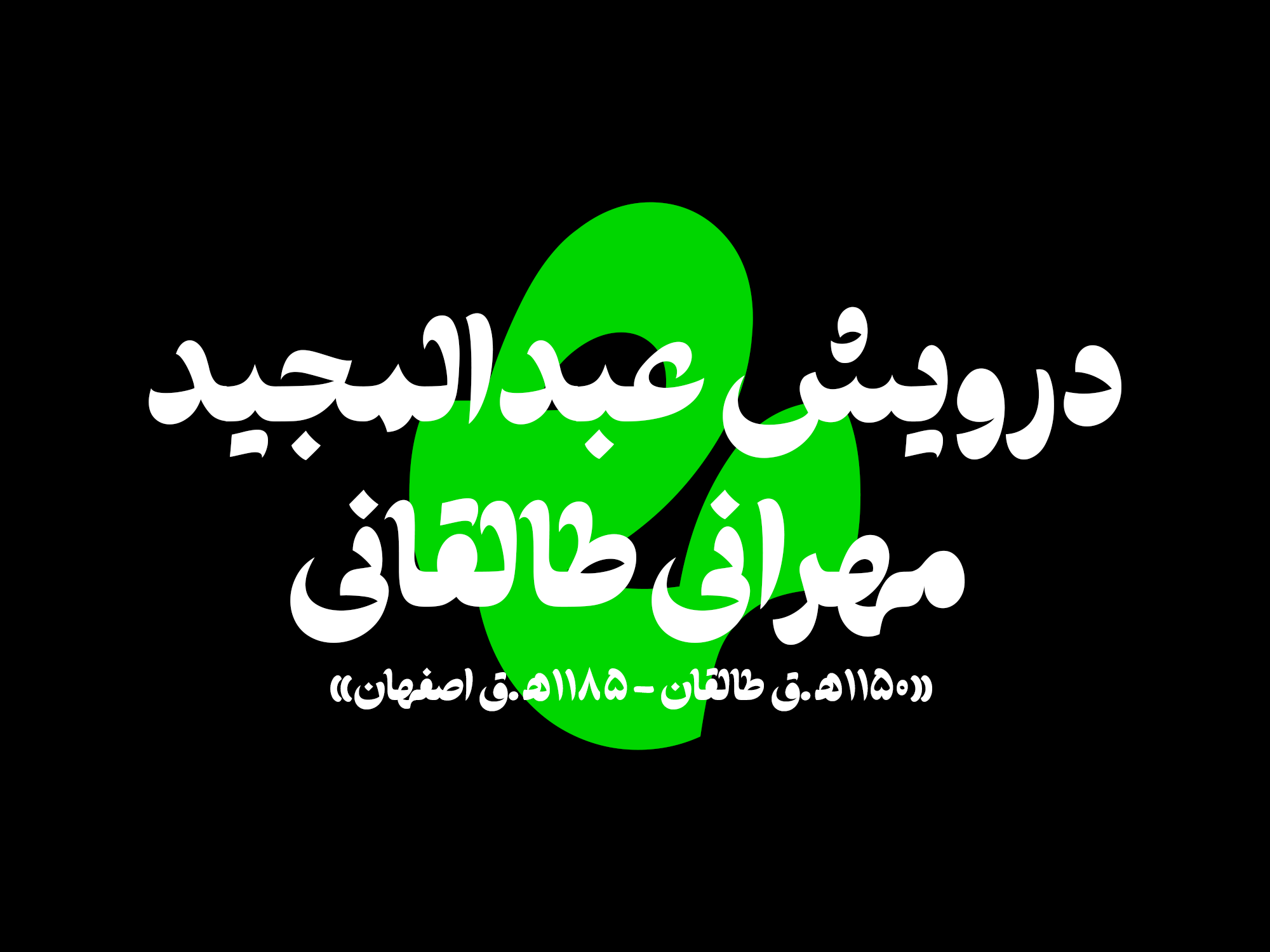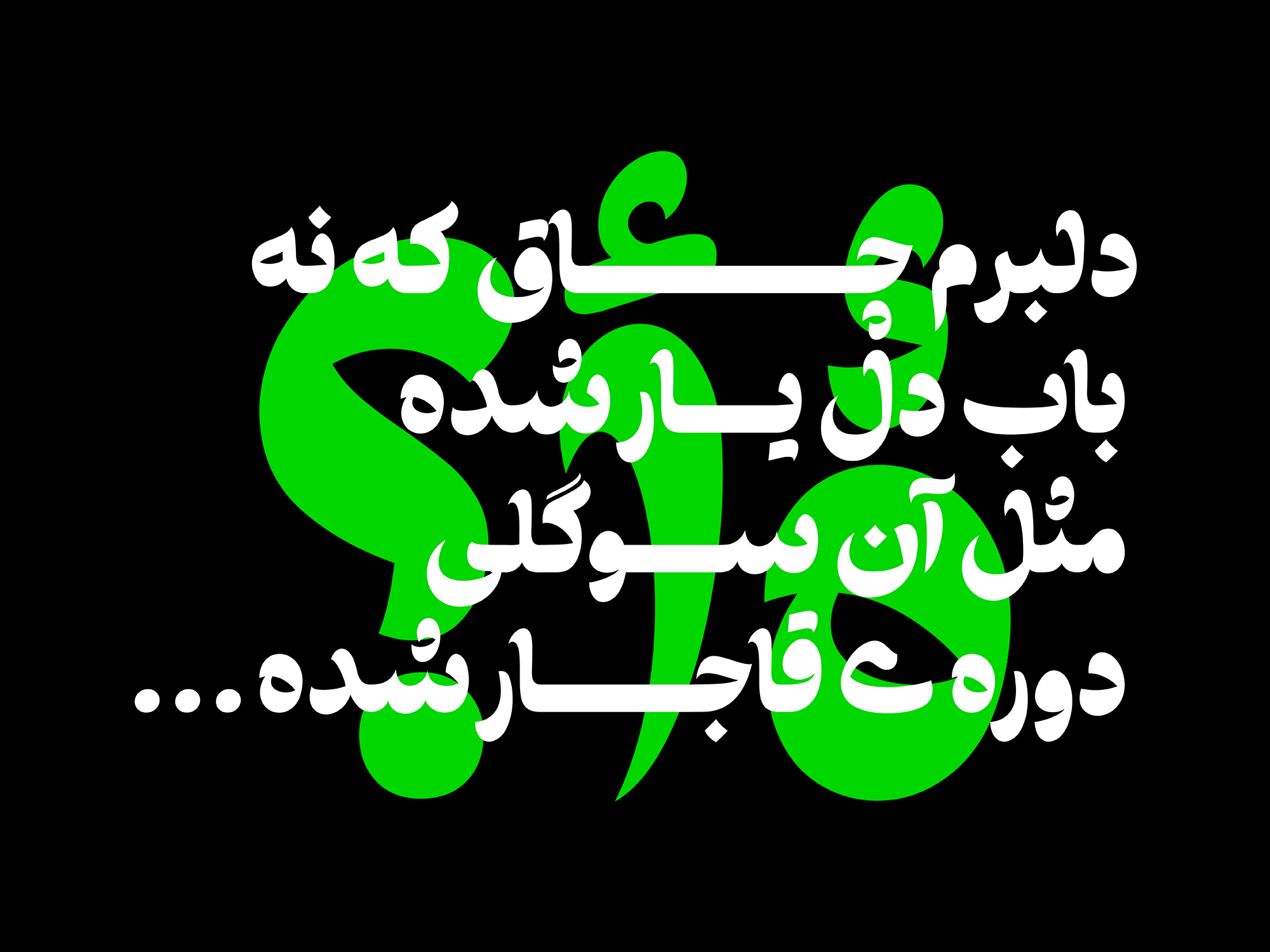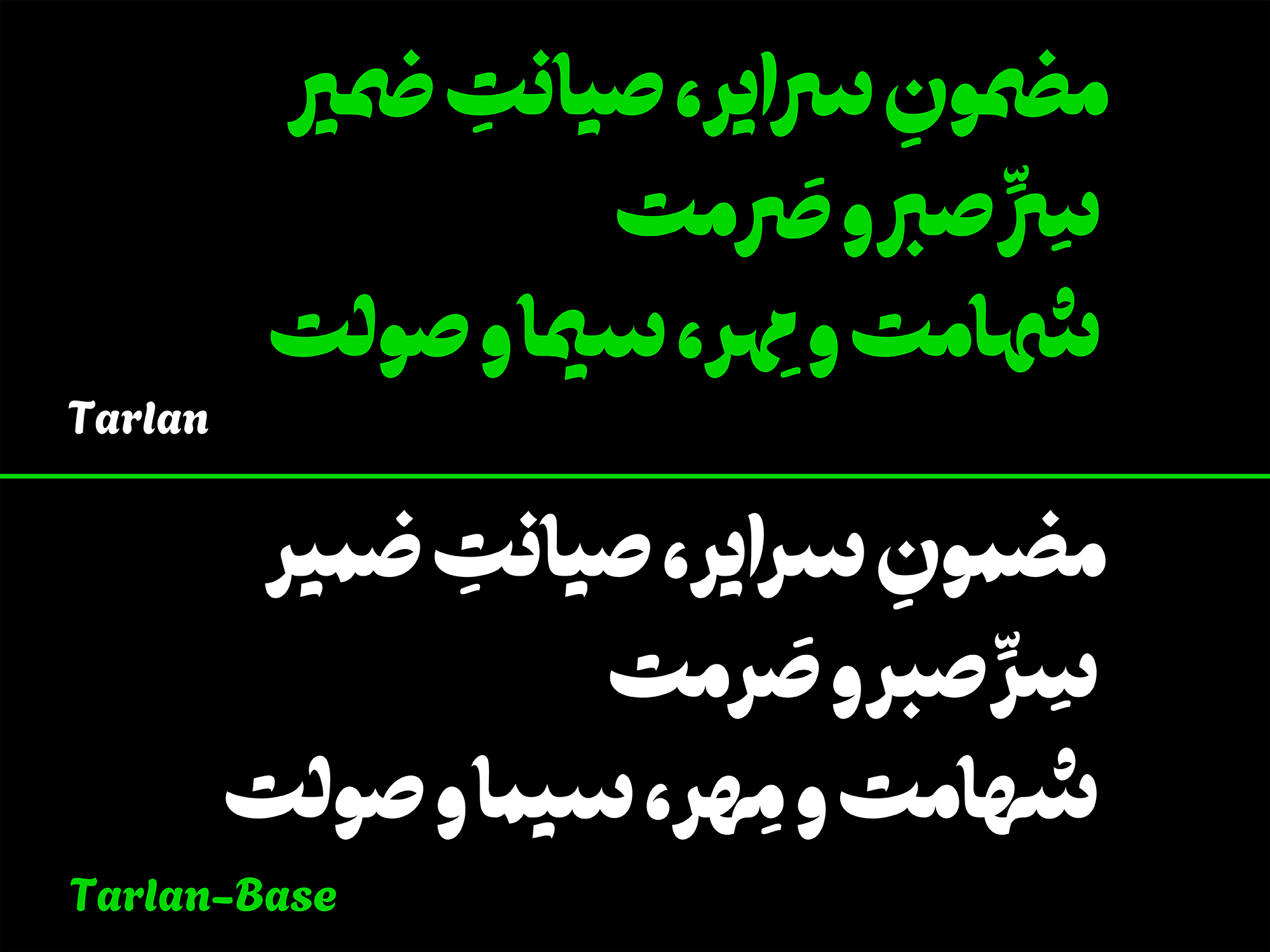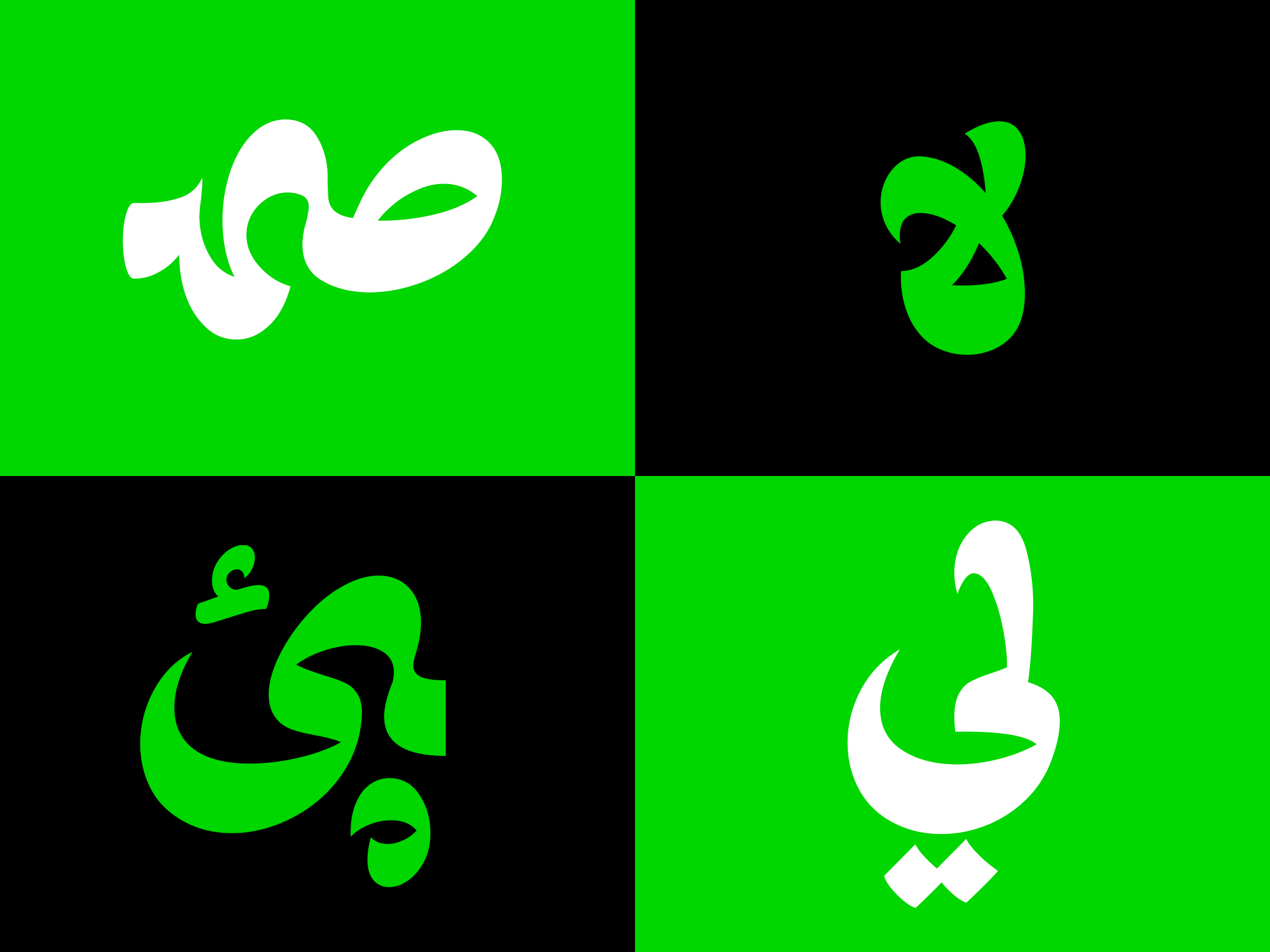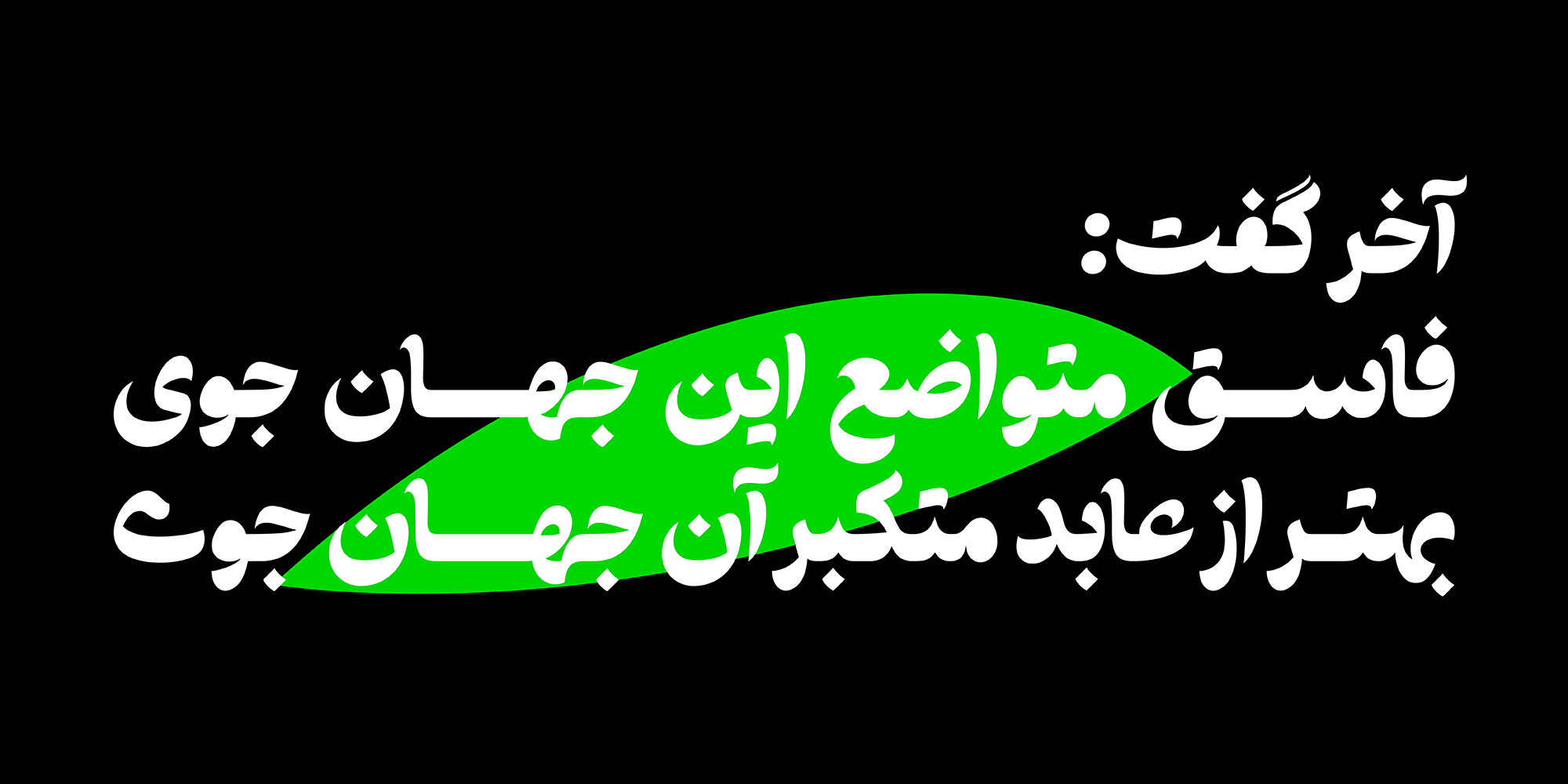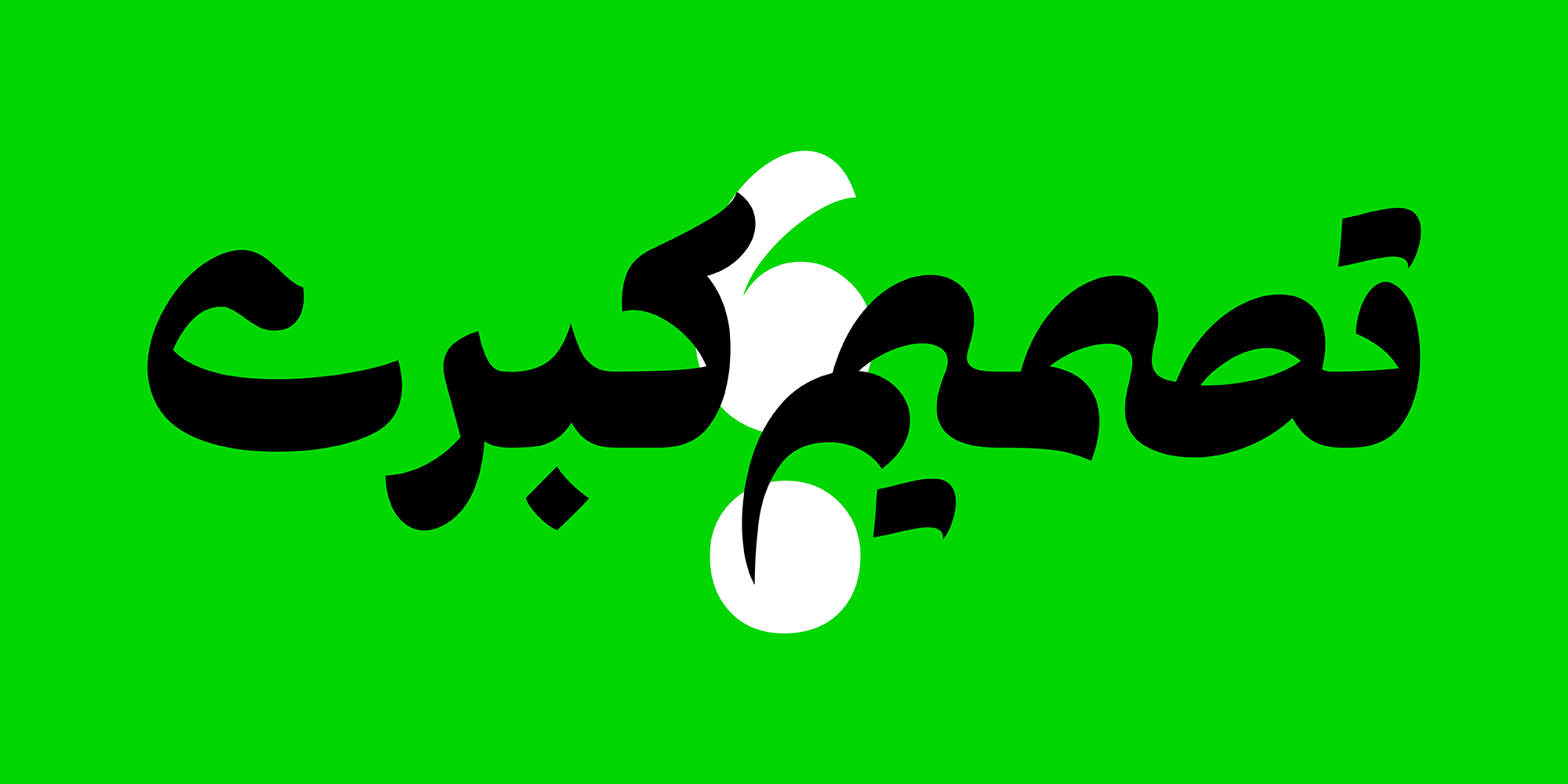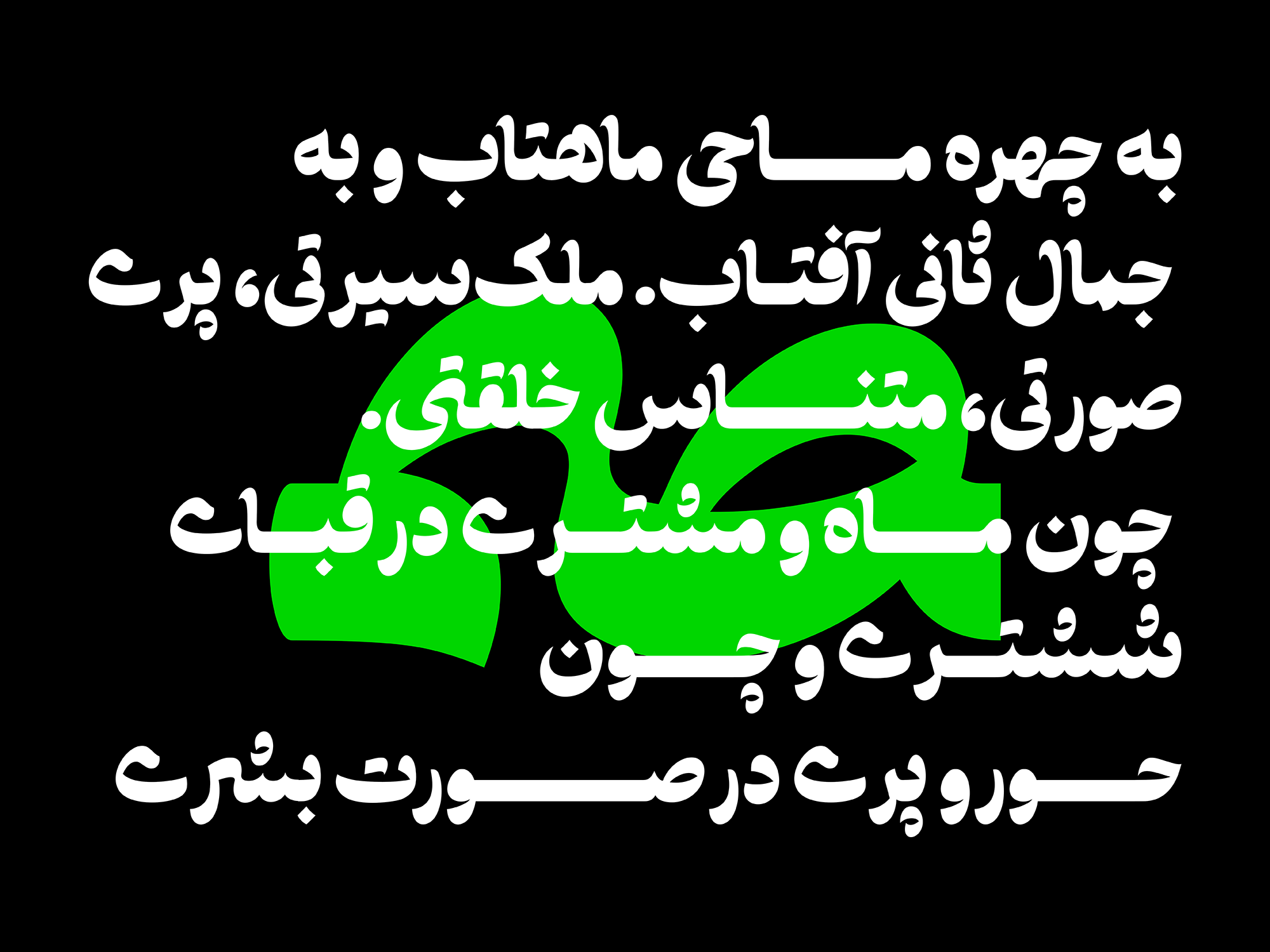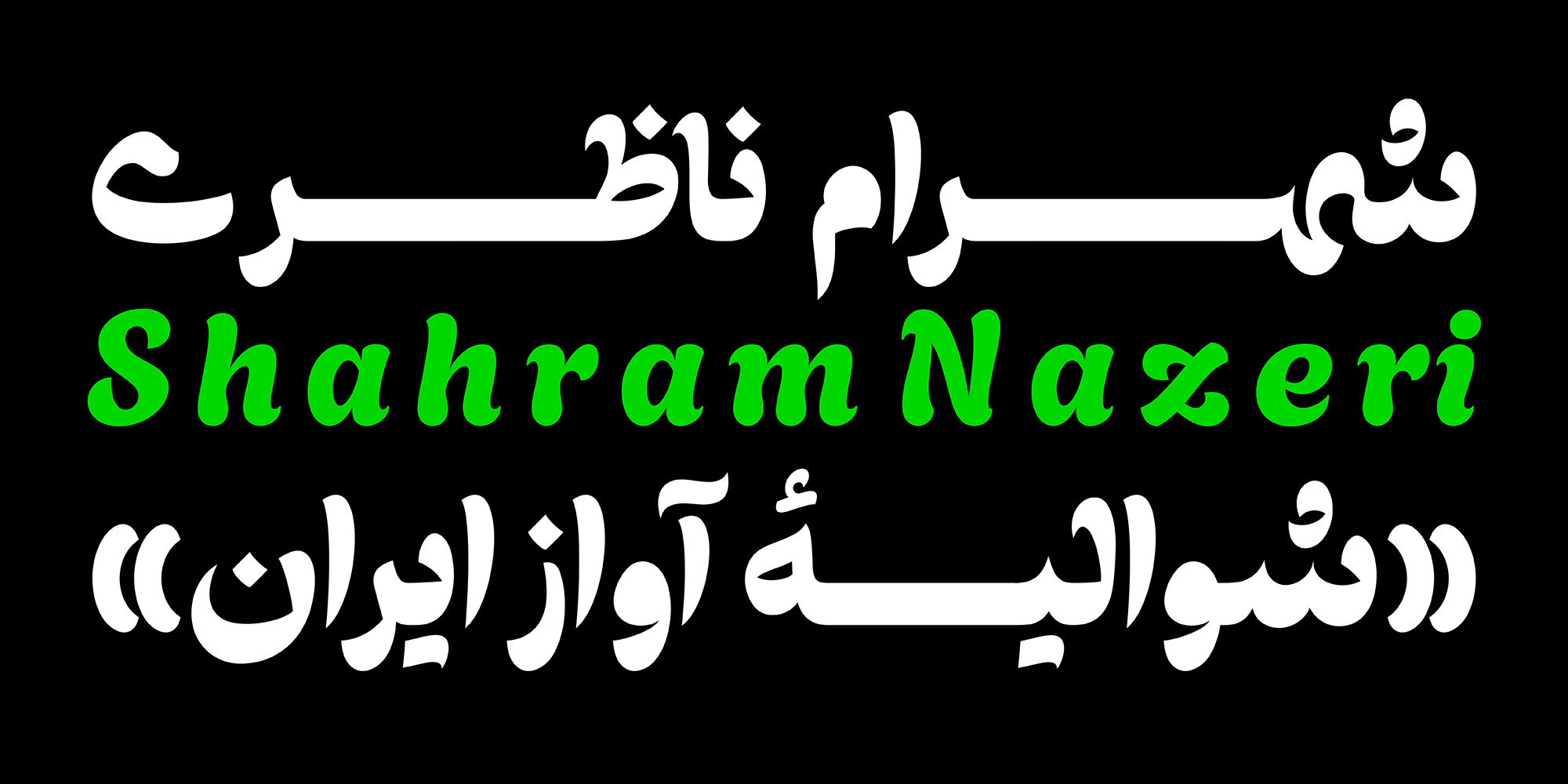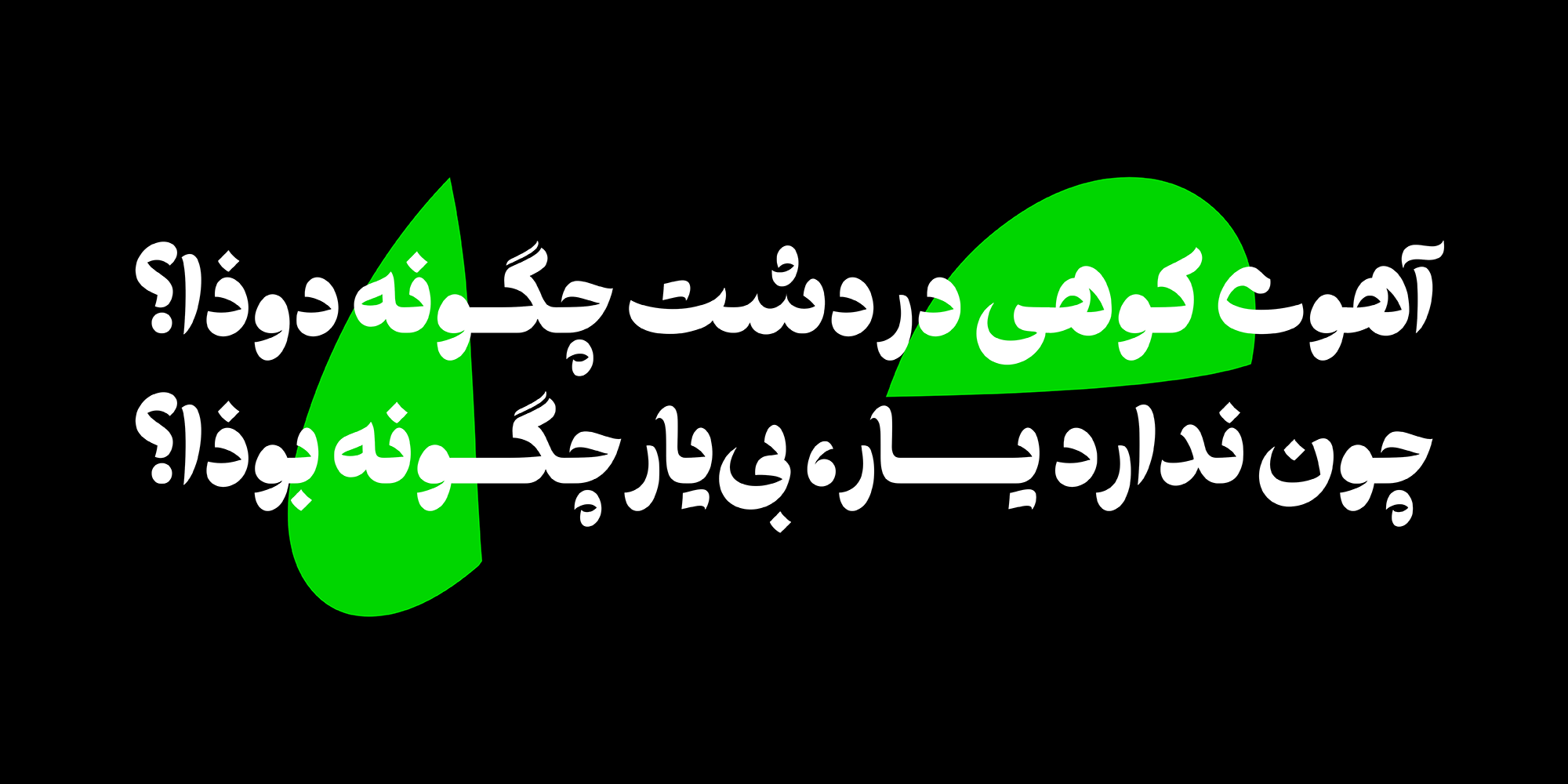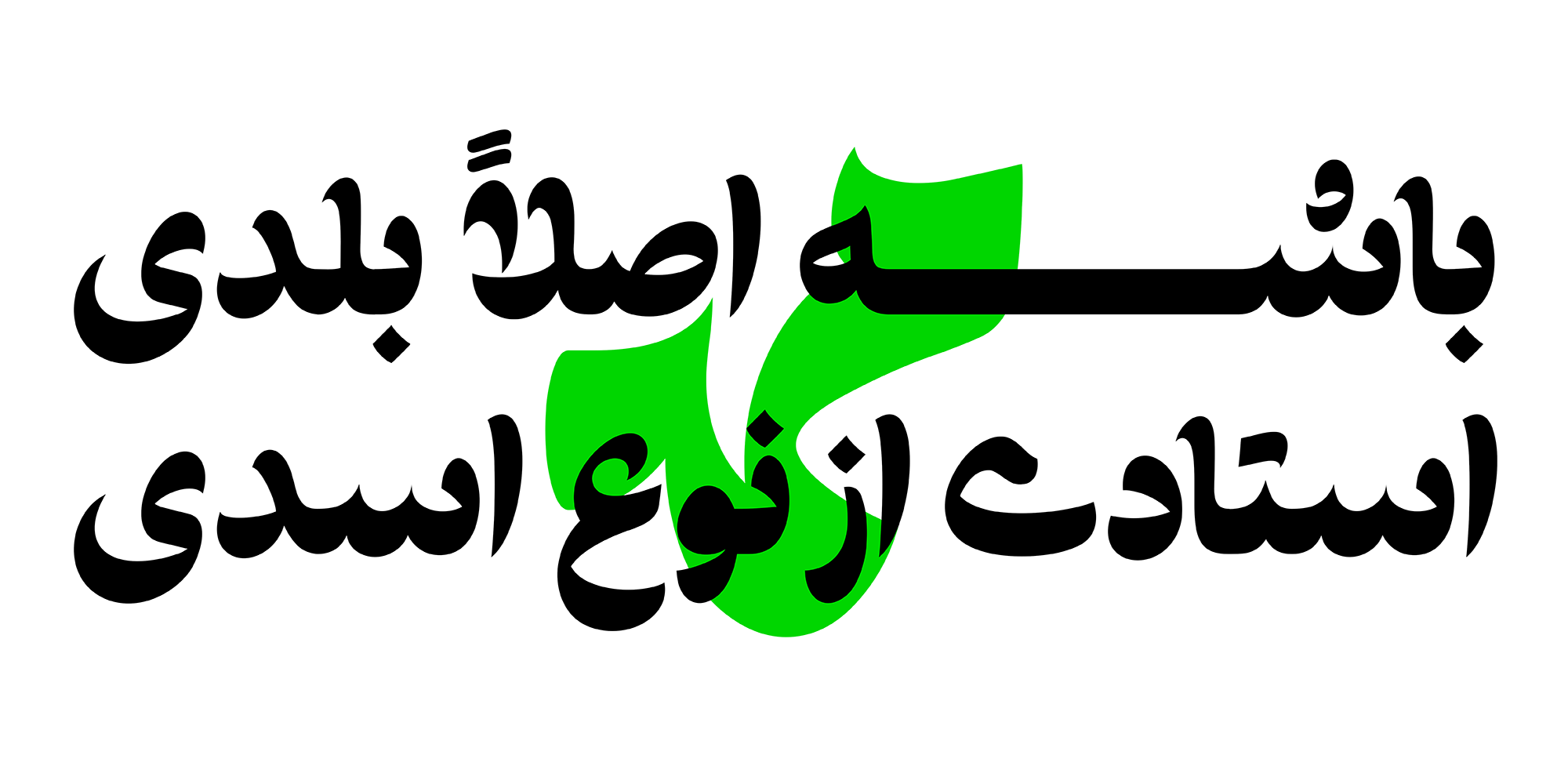
فونت طرلان شامل دو نسخه است که هرکدام برای شیوهای متفاوت از استفاده طراحی شدهاند.
1) نسخهی اصلی (TARLAN) که جایگزینها و ترکیبات هوشمند بهصورت پیشفرض در آن فعال هستند. این نسخه همان تجربهای را ارائه میدهد که در طراحی فونت مدنظر بوده است و برای استفاده در اغلب پروژهها پیشنهاد میشود.
2) نسخهای با فرمهای پایه (Tarlan Base)، بدون جایگزینها و ترکیبات خودکار. این نسخه برای کاربرانی مناسب است که ترجیح میدهند متن با فرمهای استاندارد حروف نمایش داده شود.